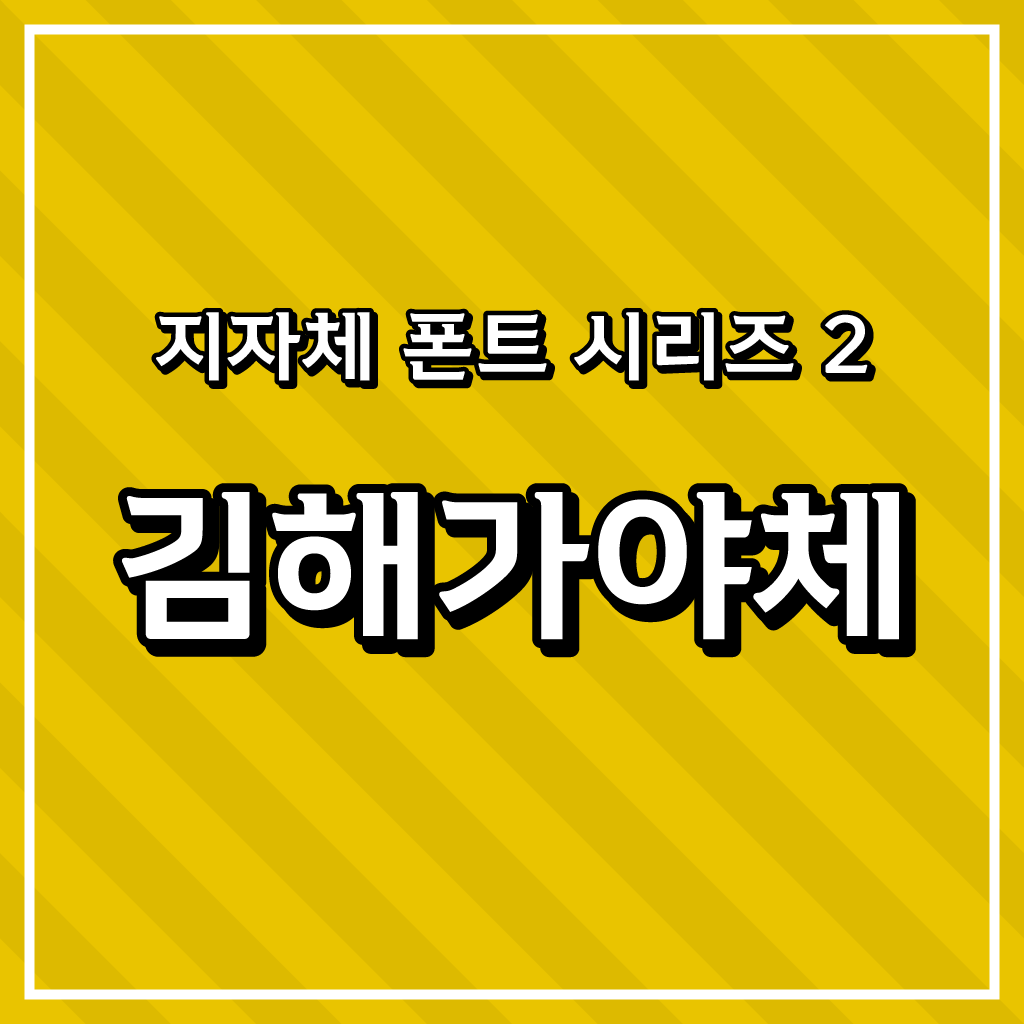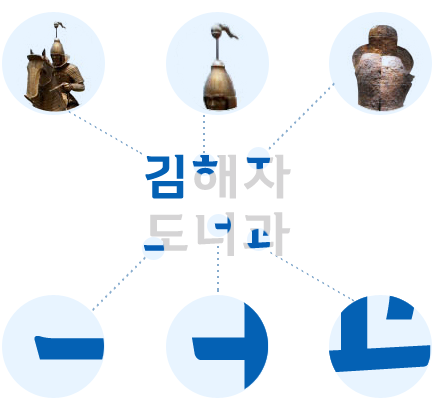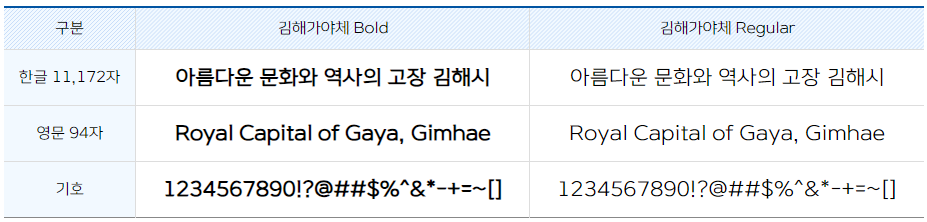
오늘은 지자체에서 제공하는 무료 폰트 시리즈 2탄, 김해시에서 제공하는 김해가야체를 소개합니다~
김해가야체
김해가야체는 가야의 기마병을 모티브로 한 서체라고 합니다. 강인하고 용맹한 인상을 보여주기 위해 단단하고 안정적인 평체 구조로 디자인되었다네요~ 'ㅎ'의 꼭지는 투구의 모습을, 'ㄱ'과 'ㄷ' 등의 자소에서 철갑옷의 단단함을 표현했다고 합니다. 전체적으로 가로줄기의 돌기와 맺음에 사선값을 줌으로, 힘차게 달리는 가야 기마병의 역동성을 담은 서체라고 합니다.
김해가야체는 Bold와 Regular가 있는데요, 한글과 영문, 다양한 기호까지 모두 지원합니다.